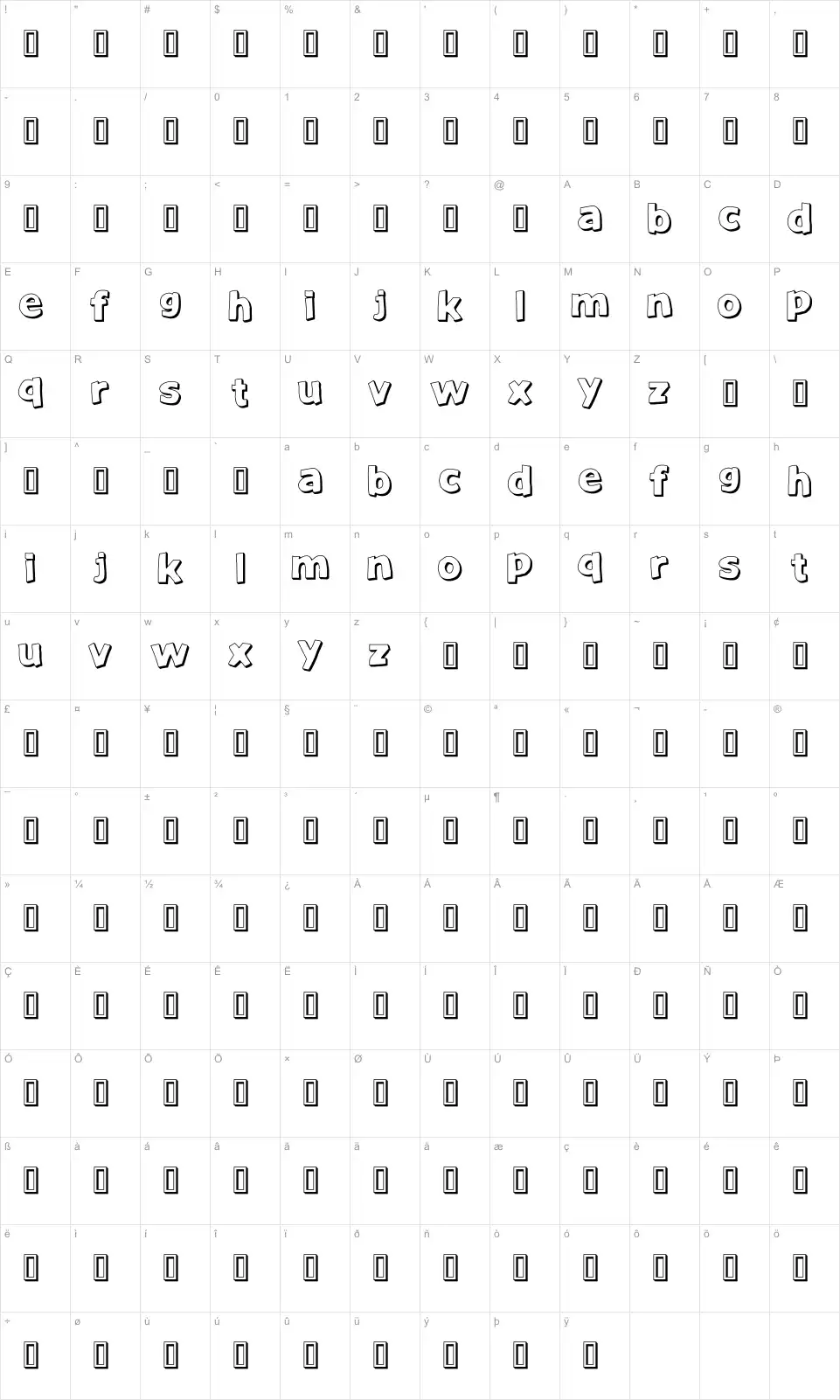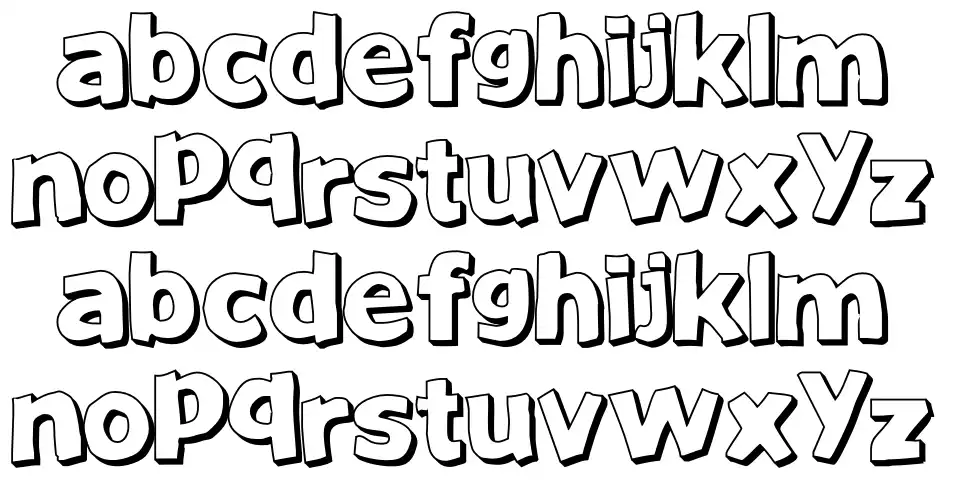
Just Another Font
A Just Another Font, criada pelo designer Pizzadude, é uma escolha ideal para projetos que buscam um toque descompromissado e divertido. Essa fonte Fancy, do gênero Cartoon, é perfeitamente adaptada para adicionar um toque personalizado aos seus materiais digitais. Se você está procurando por uma fonte divertida e criativa sem se tornar um compromisso, a Just Another Font pode ser a escolha certa. Se você quer testar como ela ficaria em seu projeto antes de usá-la, pode baixá-la ou gerar uma pré-visualização de texto personalizada online. Fornecida sob uma licença gratuita para uso pessoal, a Just Another Font é disponibilizada em formato TTF, tornando-a fácil de integrar em qualquer projeto digital. Com seu formato compacto de 10 KB, ela é leve e fácil de gerenciar. Adicionada à plataforma em 12 de julho de 2022, já são milhares de usuários que testaram e elogiaram o resultado único desta fonte. Visite o site do designer, www.pizzadude.dk, para explorar mais desenhos e personalizações de fontes criadas pelo Pizzadude.
Categoria: Fancy › Cartoon
Designer: Pizzadude